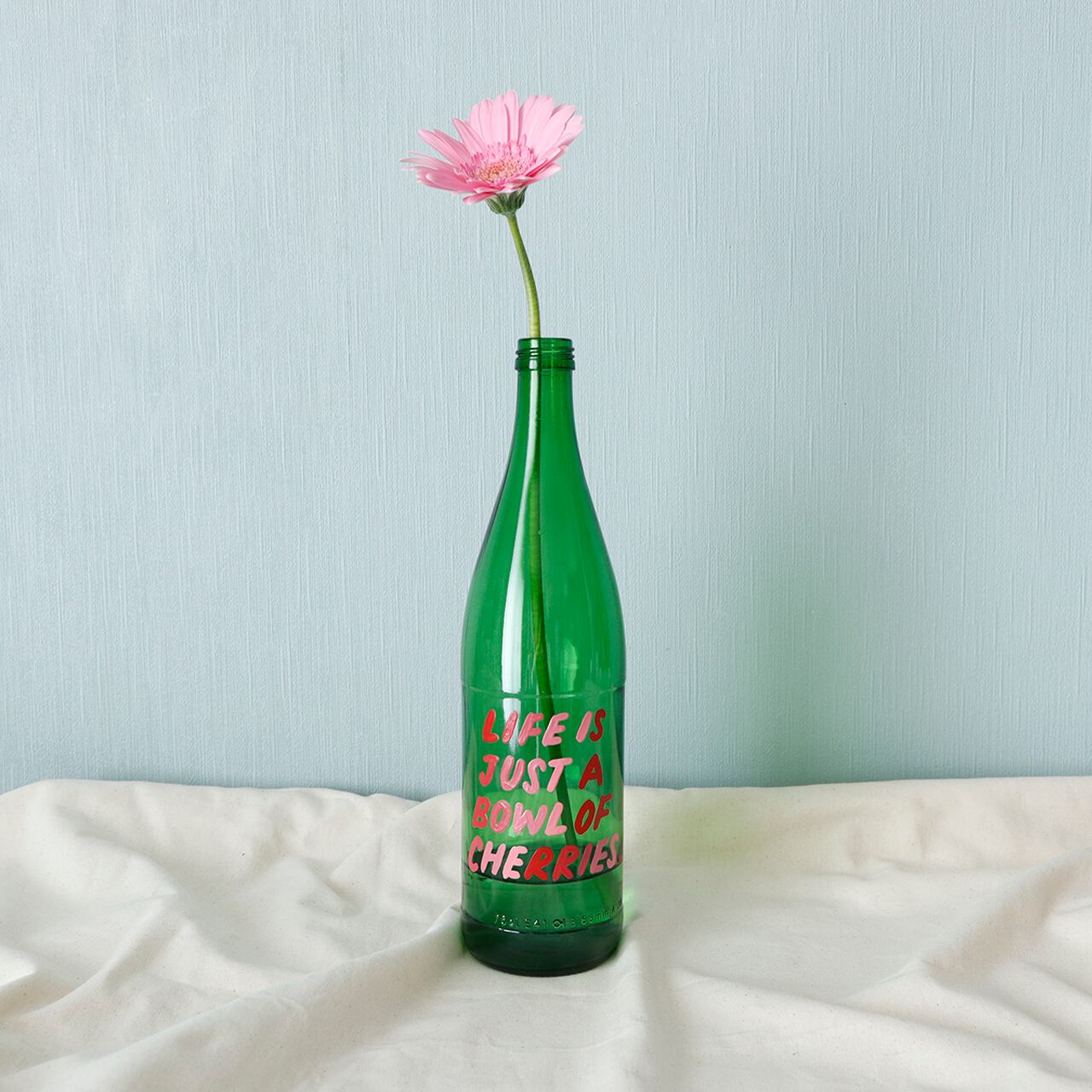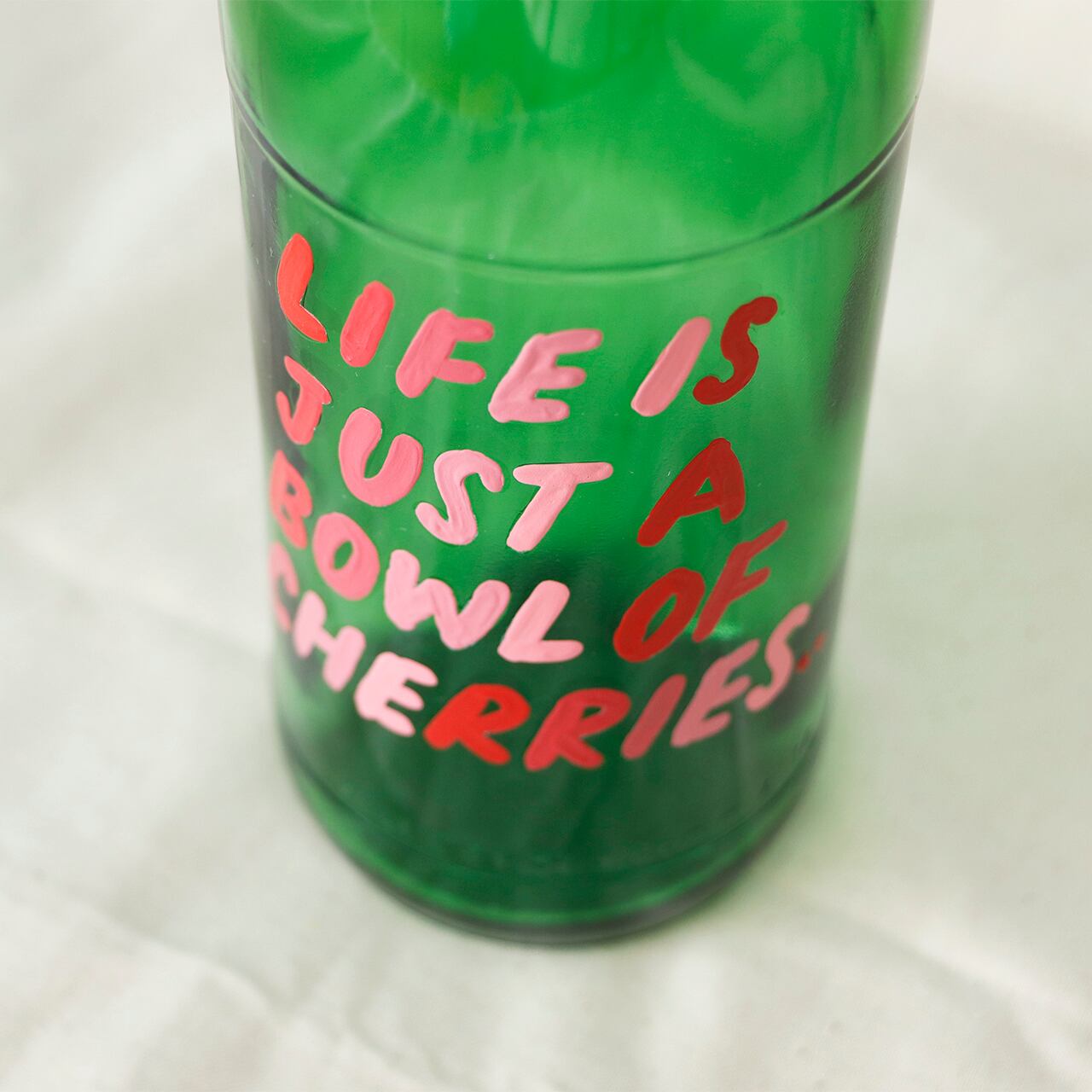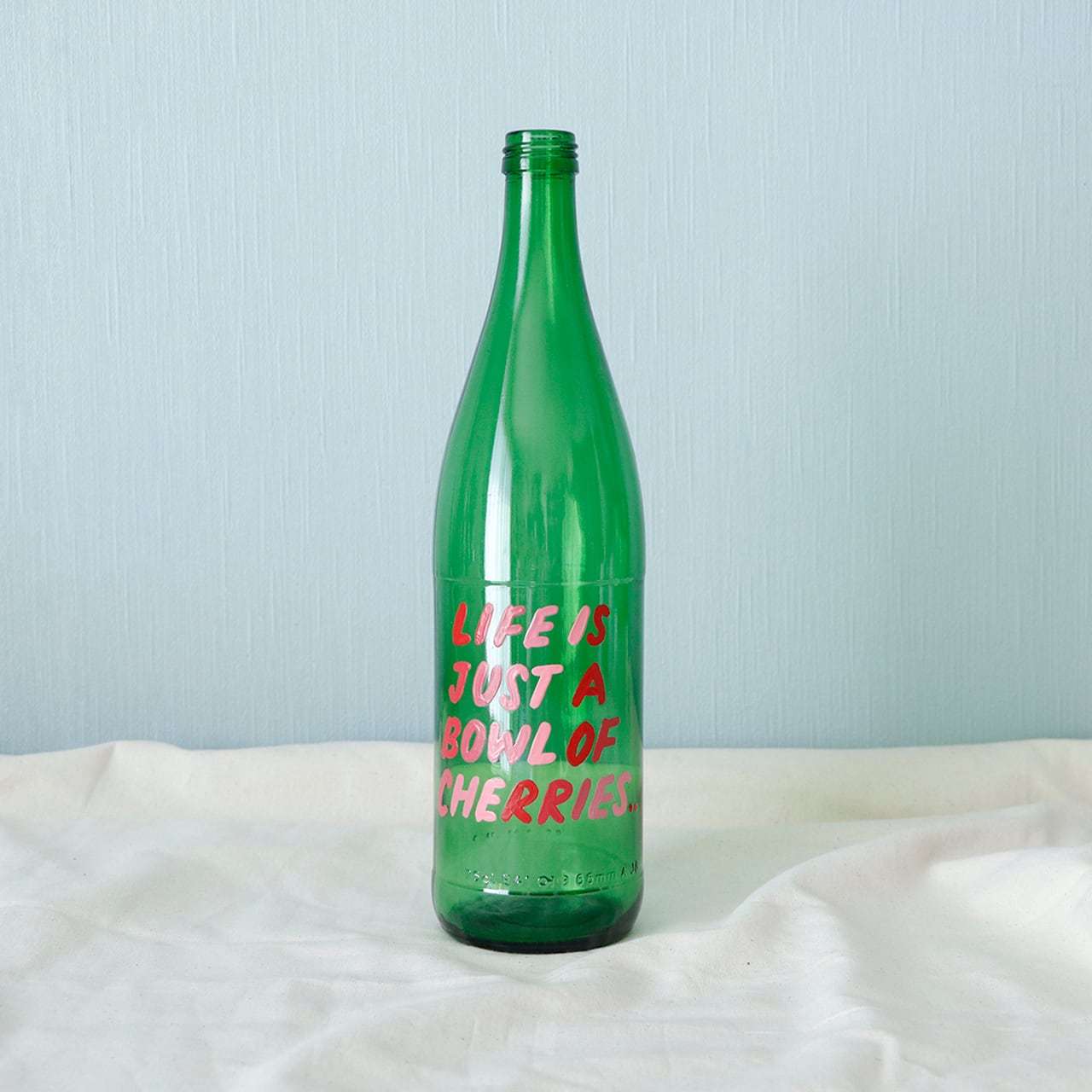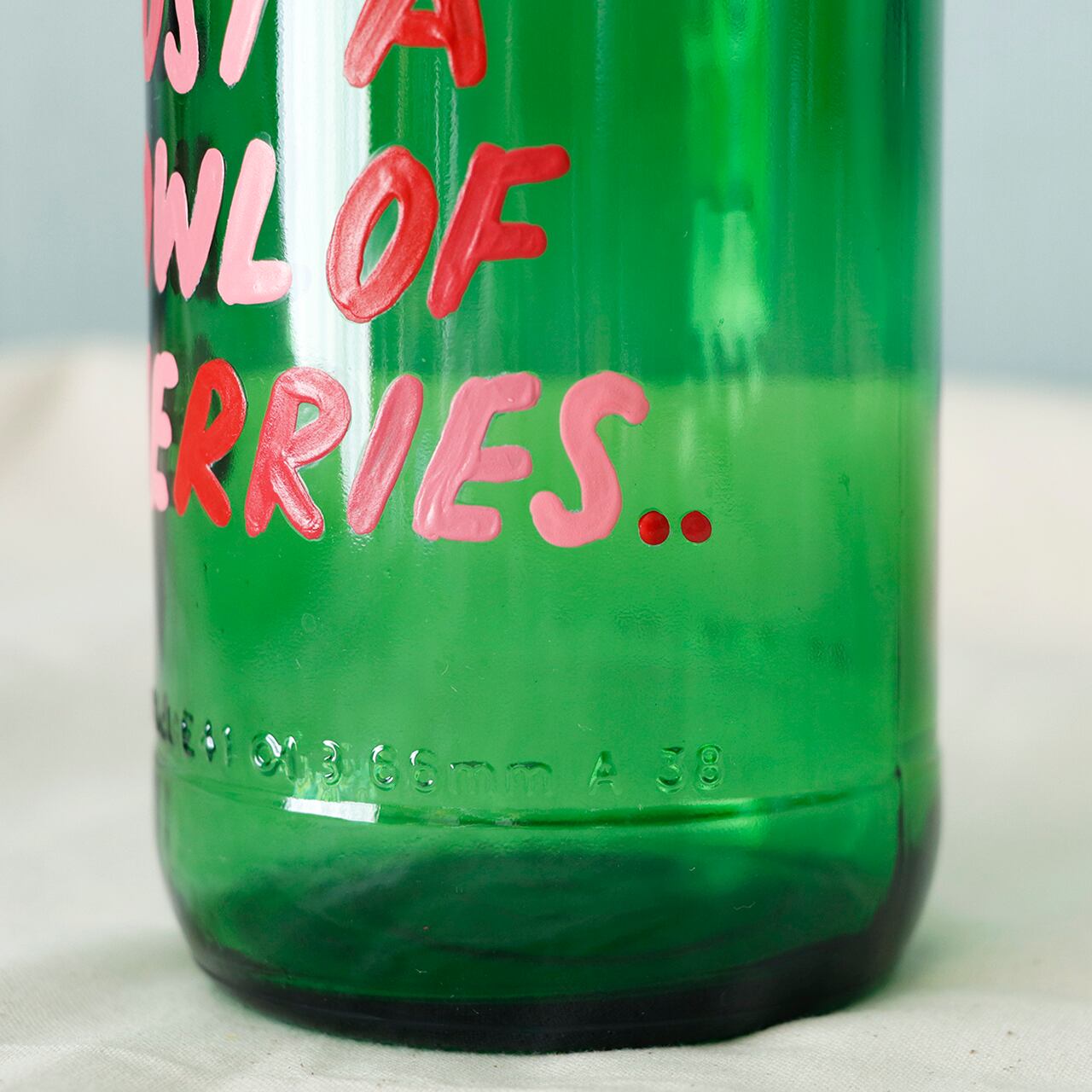
【BOTTLE PAINT ART】Life is just a bowl of cherries
Life is just a bowl of cherries
人生はボウルいっぱいに盛られたサクランボのような楽しいもの
この言葉だけでワクワクしませんか?
美味しそうなさくらんぼカラーで。
最後のピリオド2つはさくらんぼイメージです。
光が入るとこに置くと、瓶の色とともに文字も影になって素敵ですよ!!